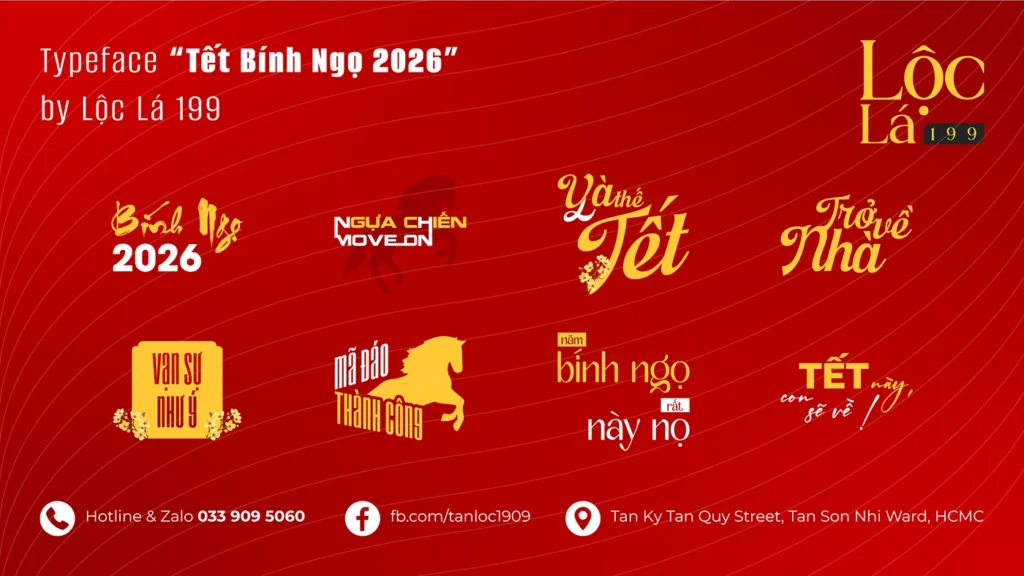
Tết Bính Ngọ 2026 đang đến gần và cộng đồng designer đã bắt đầu tìm kiếm những bộ typeface Tết độc đáo để sử dụng cho poster, banner, thiệp chúc mừng và các ấn phẩm truyền thông. Nếu bạn đang cần font Tết Bính Ngọ 2026 chuẩn đẹp, nét chữ rõ ràng, mang đậm sắc xuân thì bài viết này chính là dành cho bạn.
Typeface Tết Bính Ngọ 2026 là gì?
Typeface Tết 2026 là bộ font mang phong cách Tết cổ truyền, lấy cảm hứng từ:
-
Hình tượng Ngọ – con Ngựa trong 12 con giáp
-
Màu sắc rực rỡ của mùa xuân
-
Hoa mai, hoa đào, lồng đèn, pháo Tết
-
Chất thư pháp – Hán tự – Việt hóa
Nhờ những yếu tố này, font mang lại cảm giác lễ hội, may mắn và vô cùng phù hợp cho các chiến dịch quảng cáo dịp đầu năm.
Lợi ích khi dùng Typeface Tết Bính Ngọ 2026